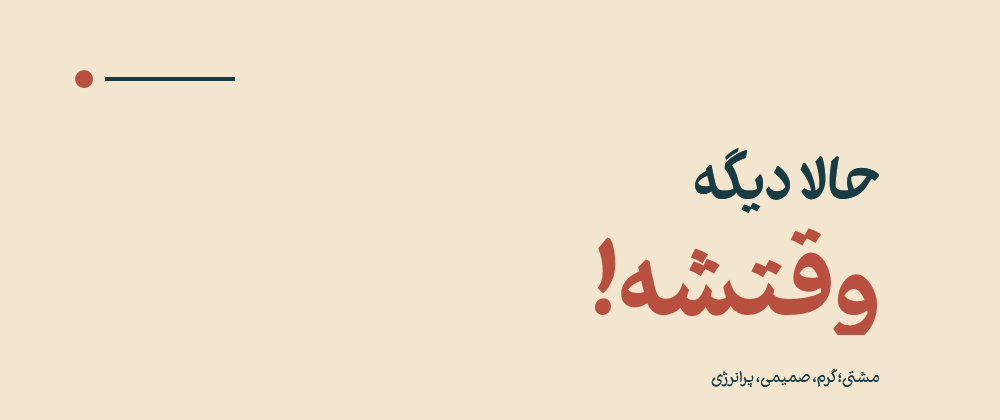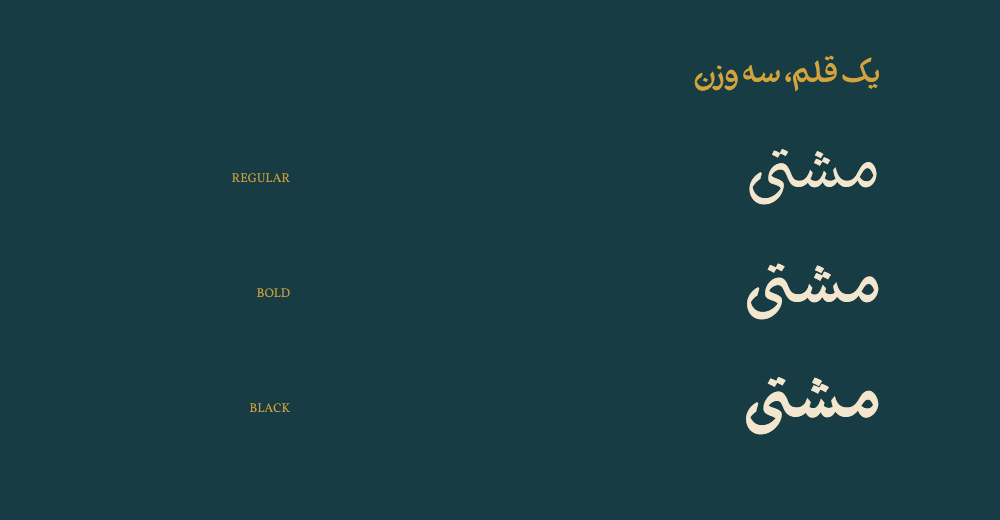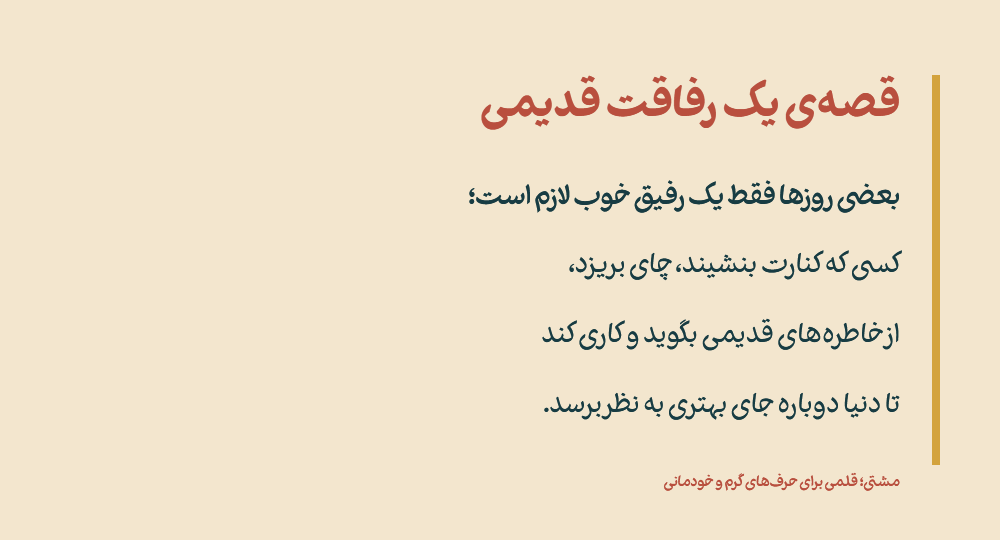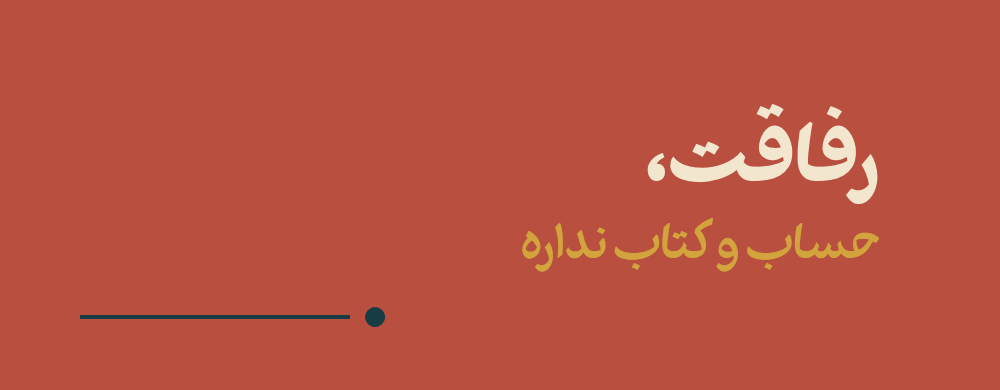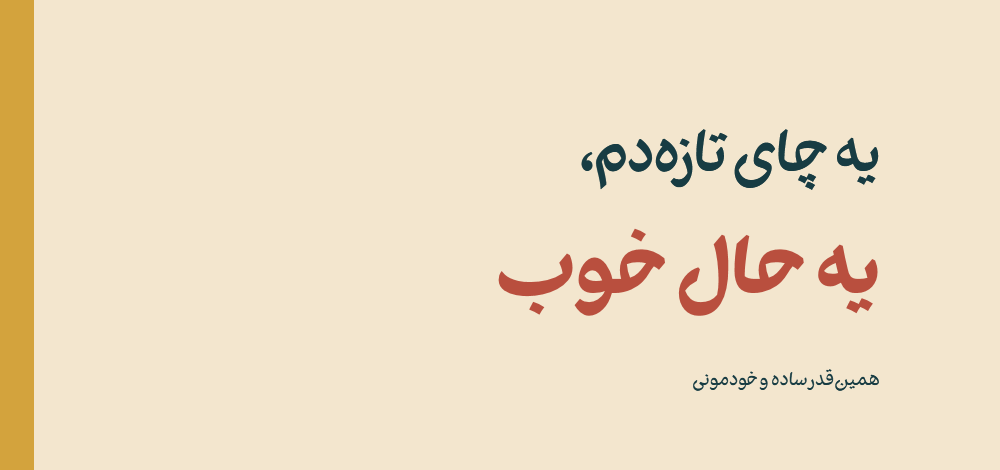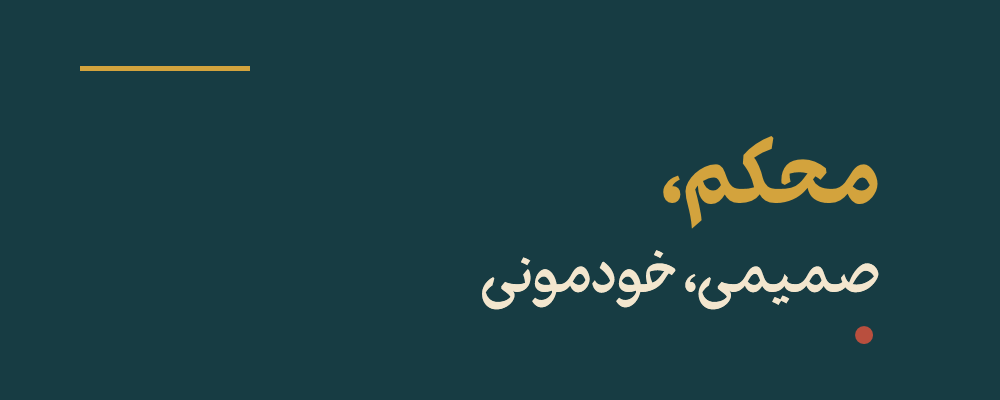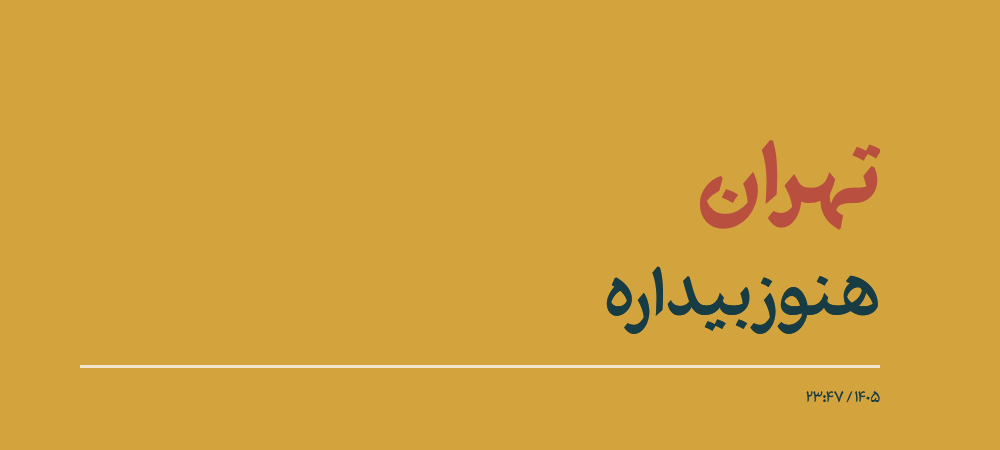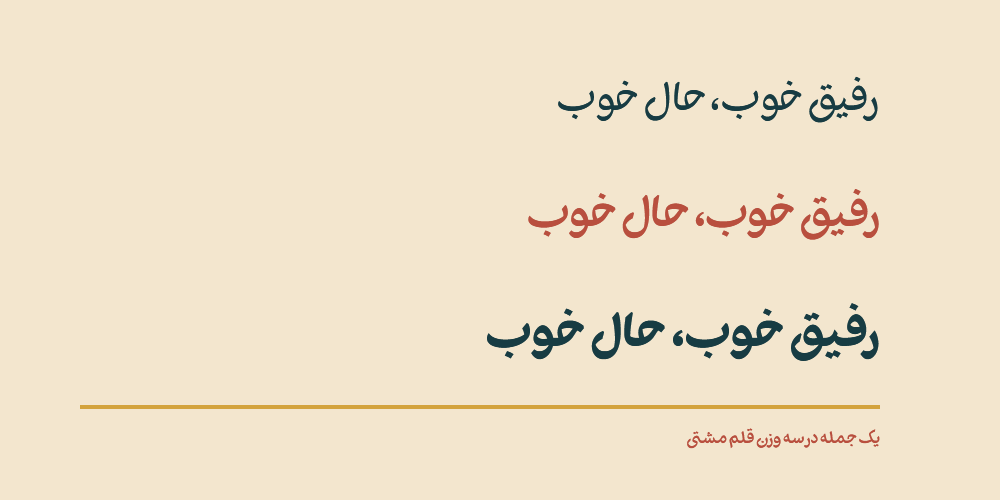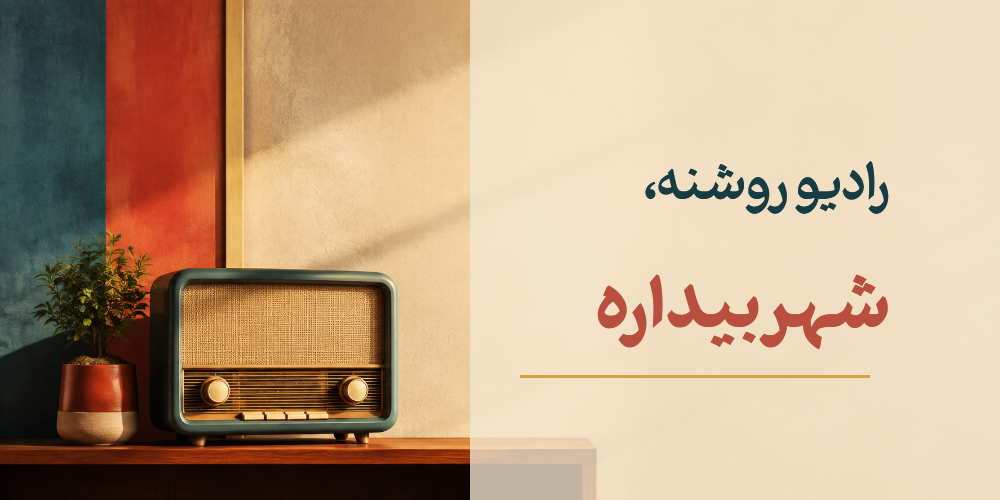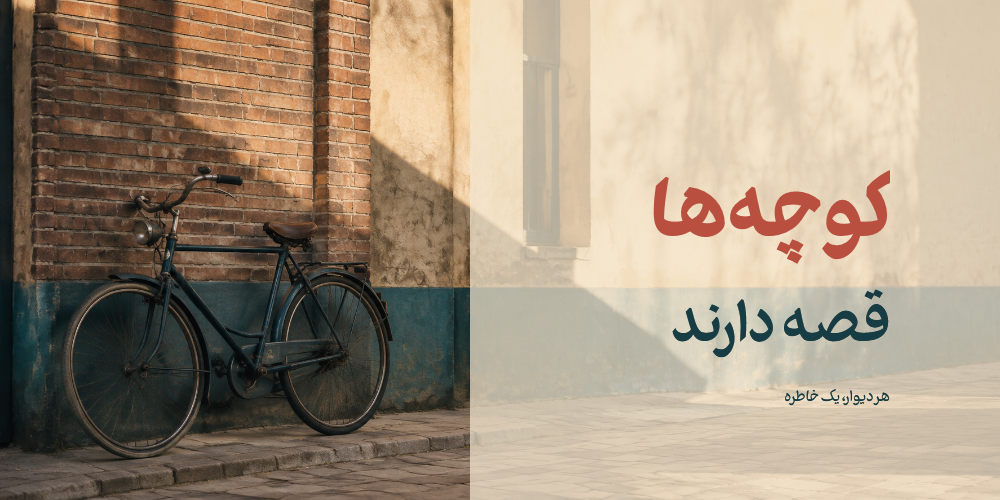
درباره قلم مشتی
برای طراحی قلم مشتی و یافتن شخصیت و ویژگیهای فرمی آن سراغ عمومیترین خطوط ایرانی-عربی (نستعلیق و رقعه) رفتم تا با استفاده از این خطوط، قلمی متناسب با فرهنگ ایرانی طراحی شود که در بافت شهری پاسخگوی نیازهای بصری نوشتاری جامعه باشد؛ قلمی که بتواند قشری از مردم ایران را راضی به استفاده نماید که همیشه خط نستعلیق را در کوچهپسکوچه شهری نسبت به قلمهای دیجیتالی ترجیح میدهند. از روحیات این قلم میتوان نسبتا نستالژیک، بیآلایش، جوان و با انرژی را برشمرد و از ویژگیهای فرمی به پر دور بودن، اندام درشت، قد متوسط، محدود نبودن به کرسی، نسبتا مایل و چشمهای متوسط اشاره کرد.
قلم مشتی در مسابقه نخستین سالانهی هنر طراحی کتاب ایران در سال ۹۴ شایستهی تقدیر شناخته شد.
میلاد داداش زاده
متولد ۱۳۶۷ اردبیل | کارشناسی رشته ارتباط تصویری از دانشکده فنی انقلاب اسلامی | طراح گرافیک، طراح قلم و خوشنویس | مدیر هنری شرکت تبلیغاتی مان ۱۳۹۳ | طراح ارشد گرافیک اتحادیه ناشران و کتابفروشان تهران ۱۳۸۷ تا ۱۳۹۰ | چاپ آثار در کتابهای گرافیک ۳، ۵ و تایپوگرافی ایرانی | راهیابی اثر به نمایشگاه طراحی لوگوی همکاران سیستم ۱۳۸۷ | اولین نمایشگاه انفرادی لوگو و لوگوتایپ در سال ۱۳۹۰